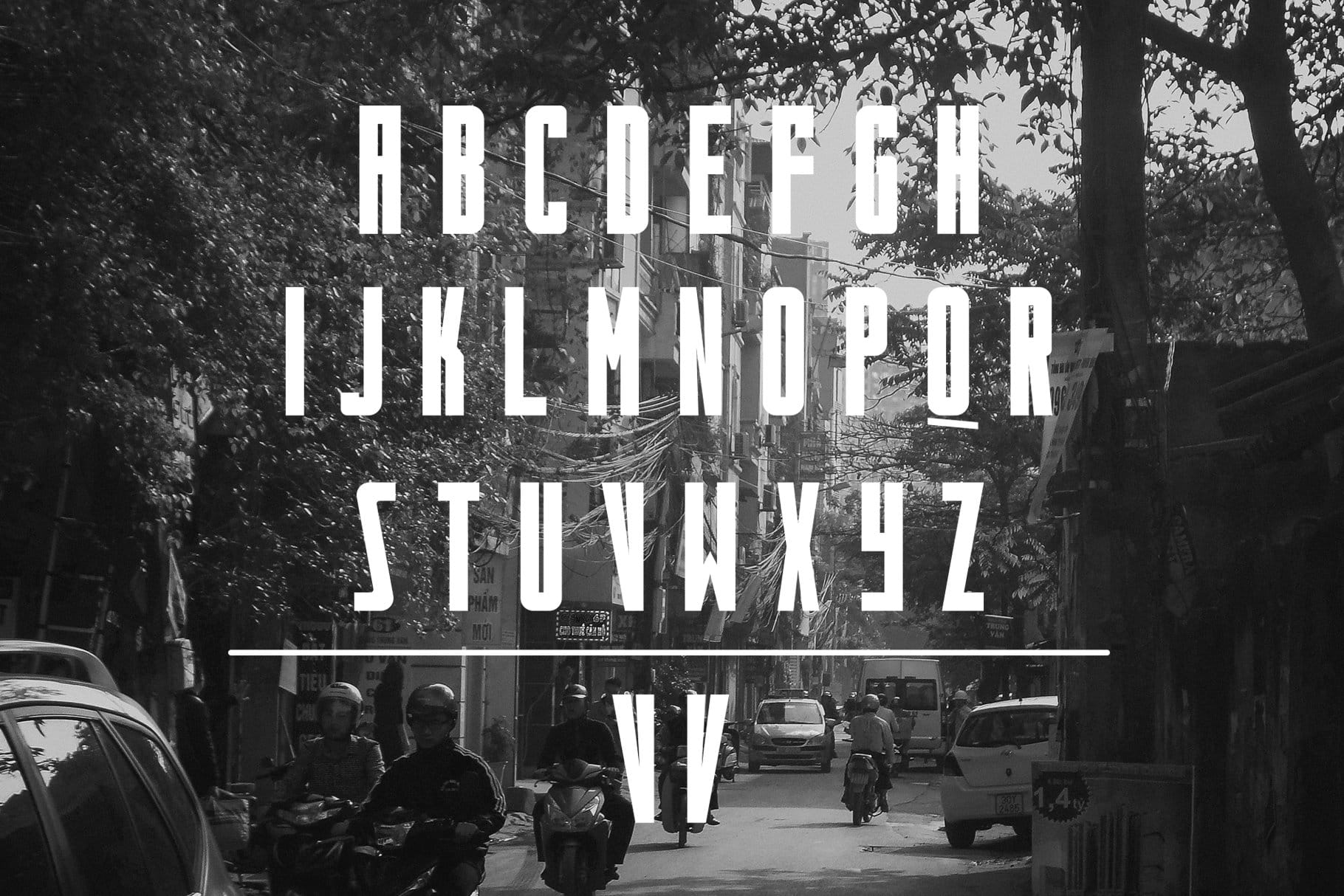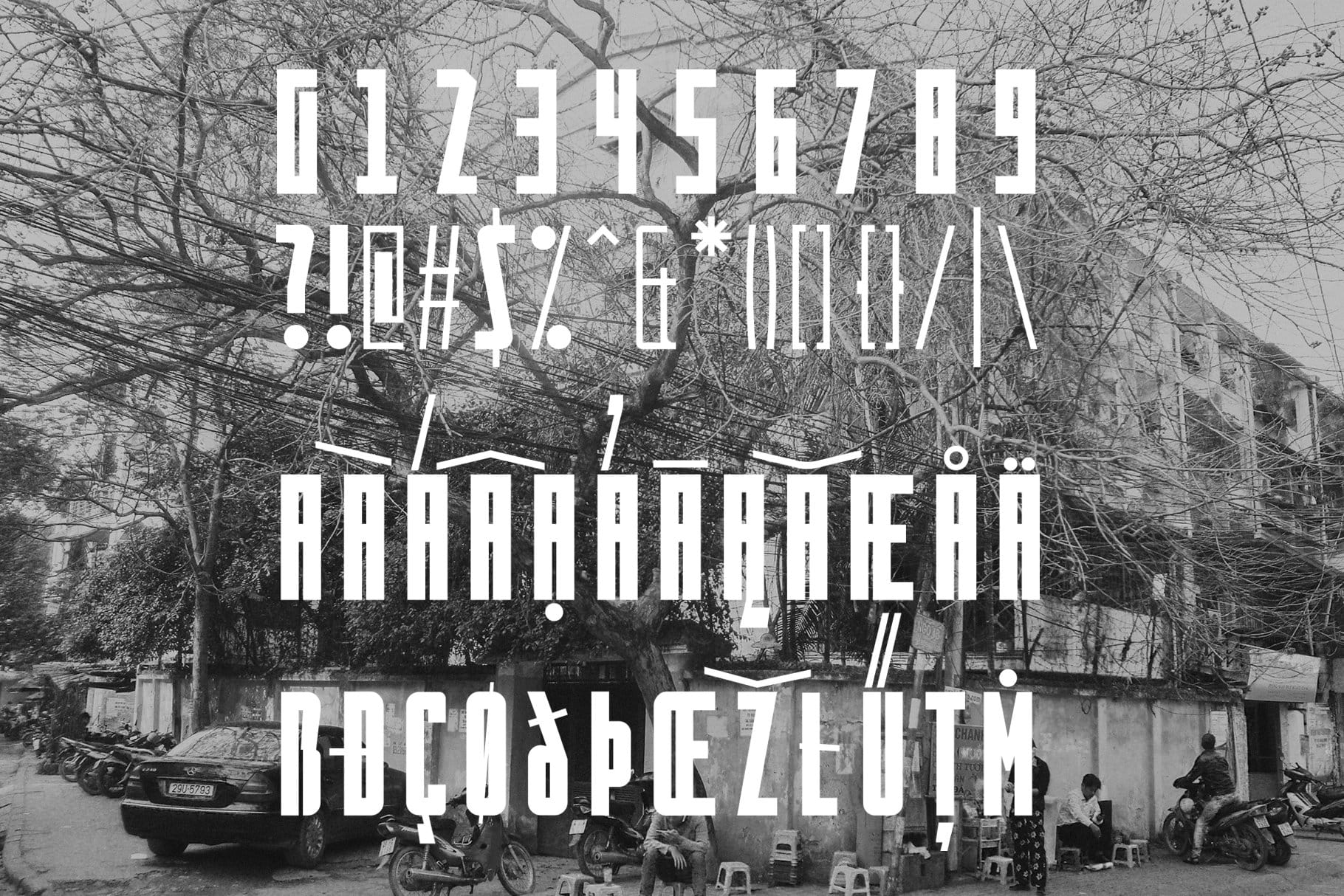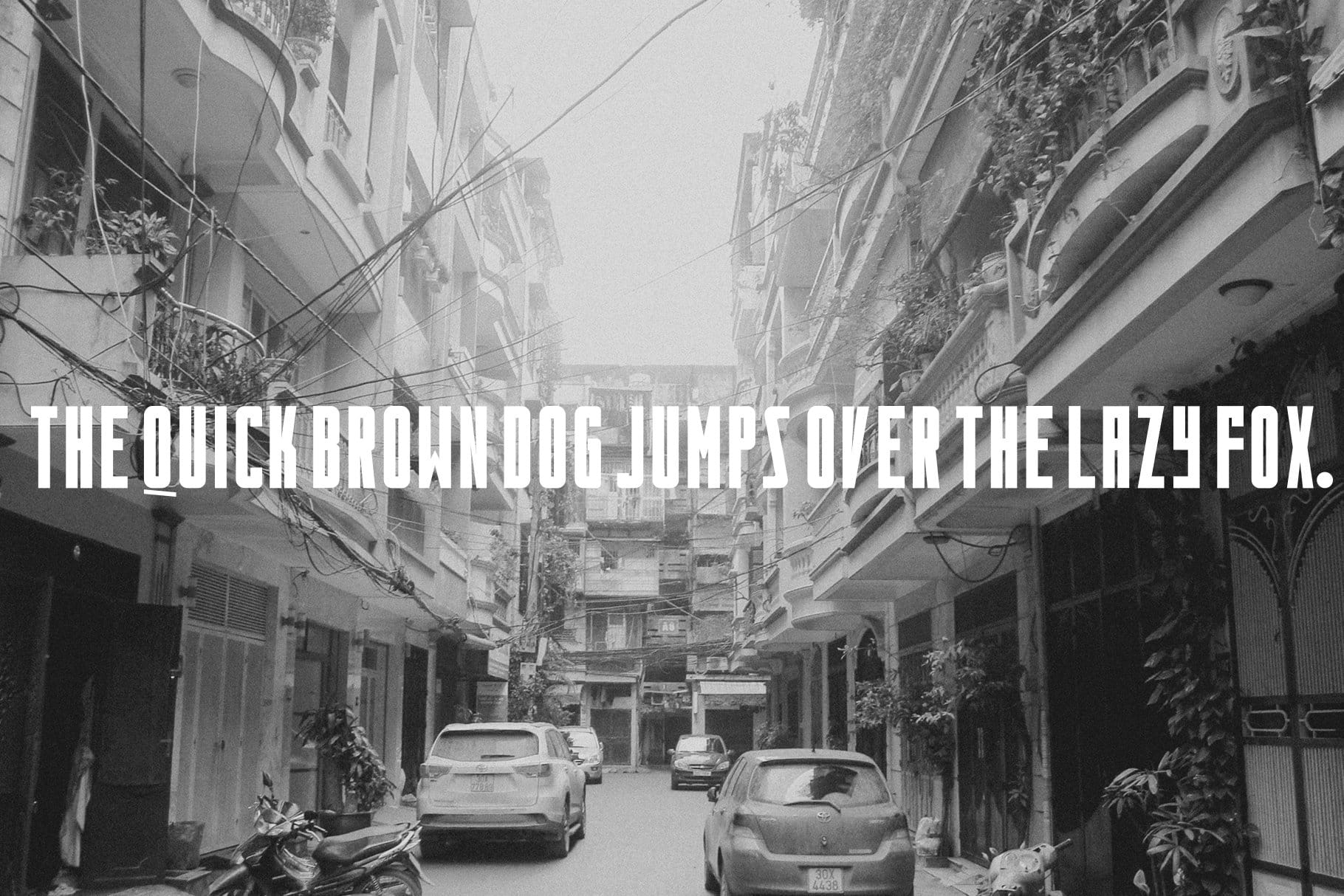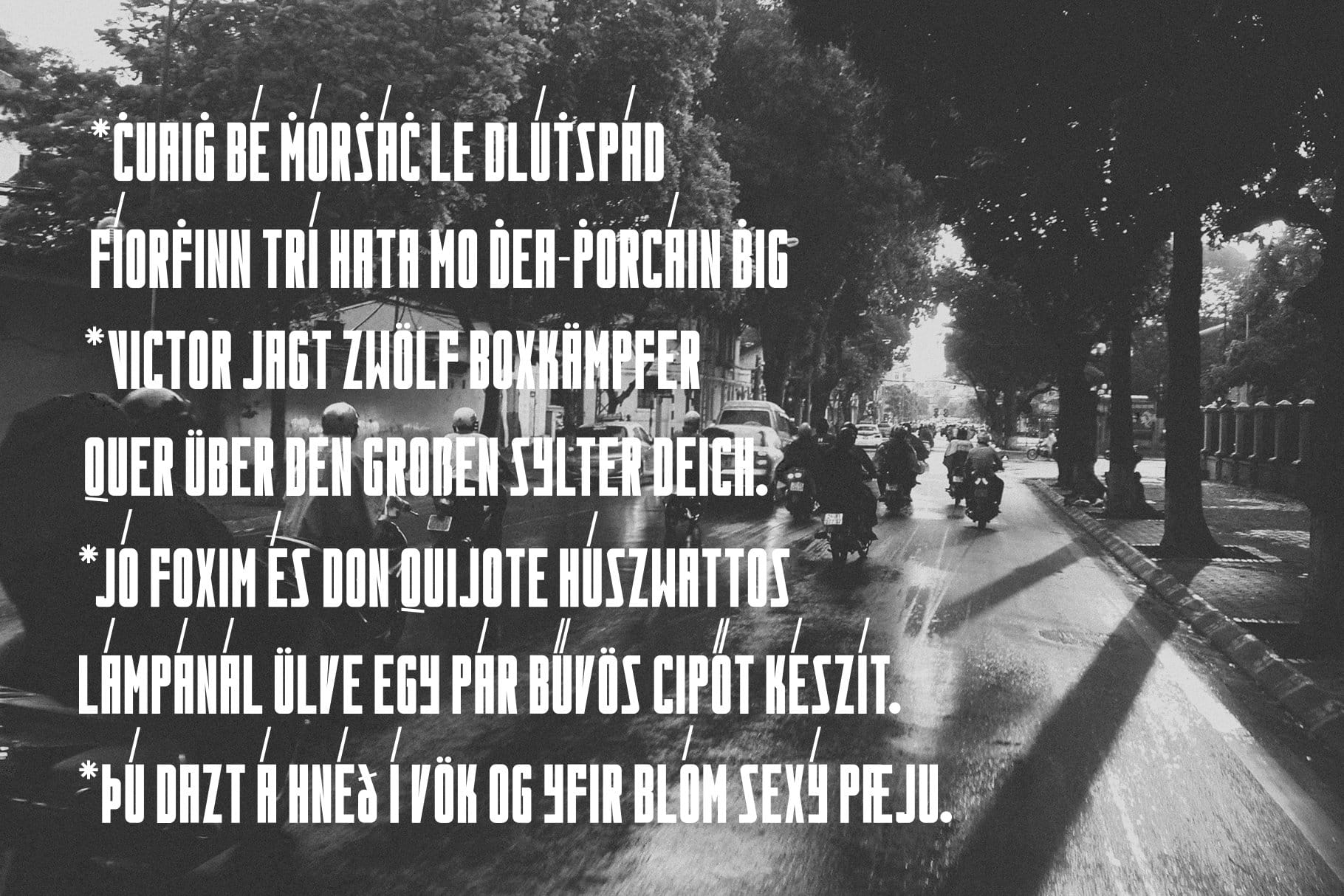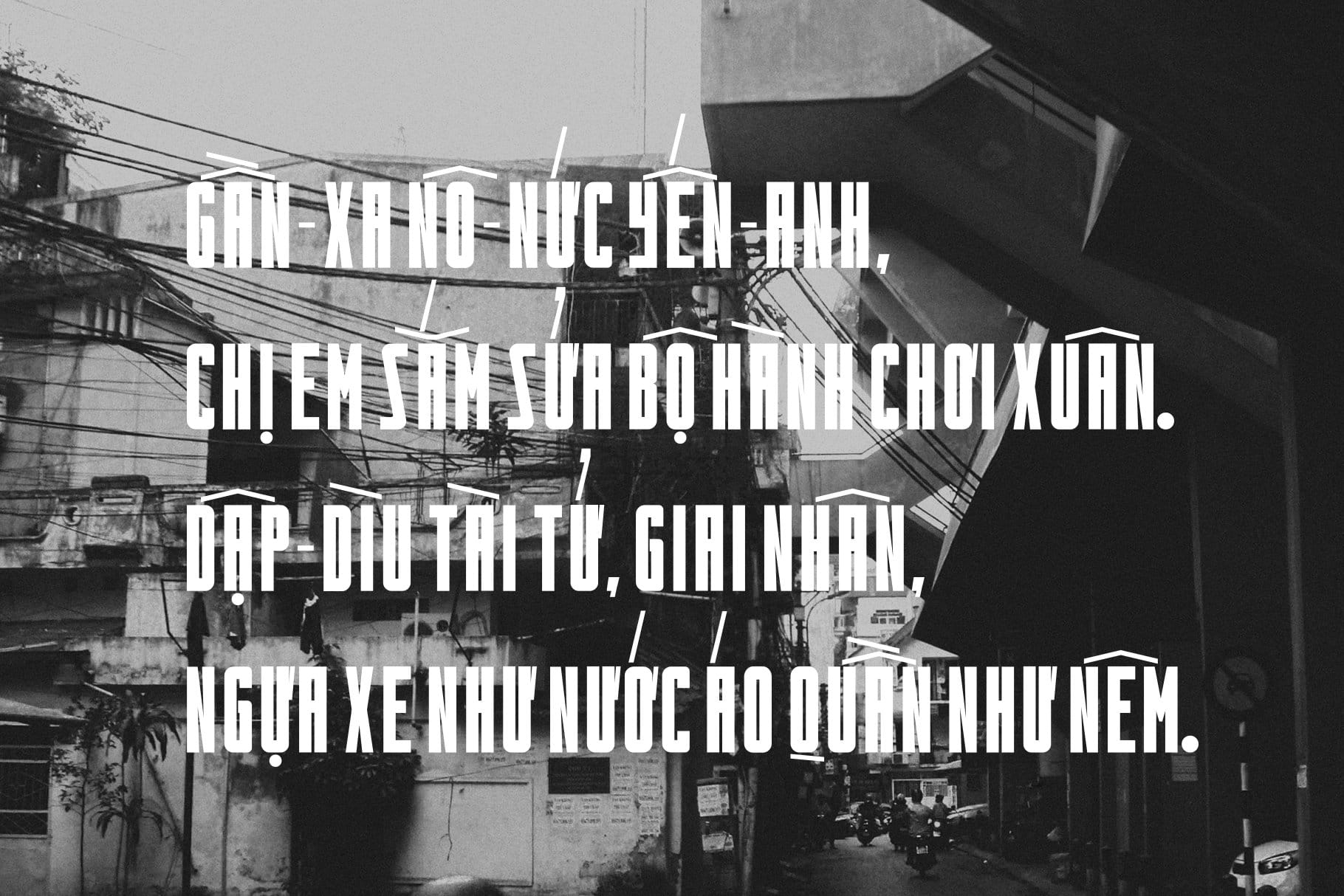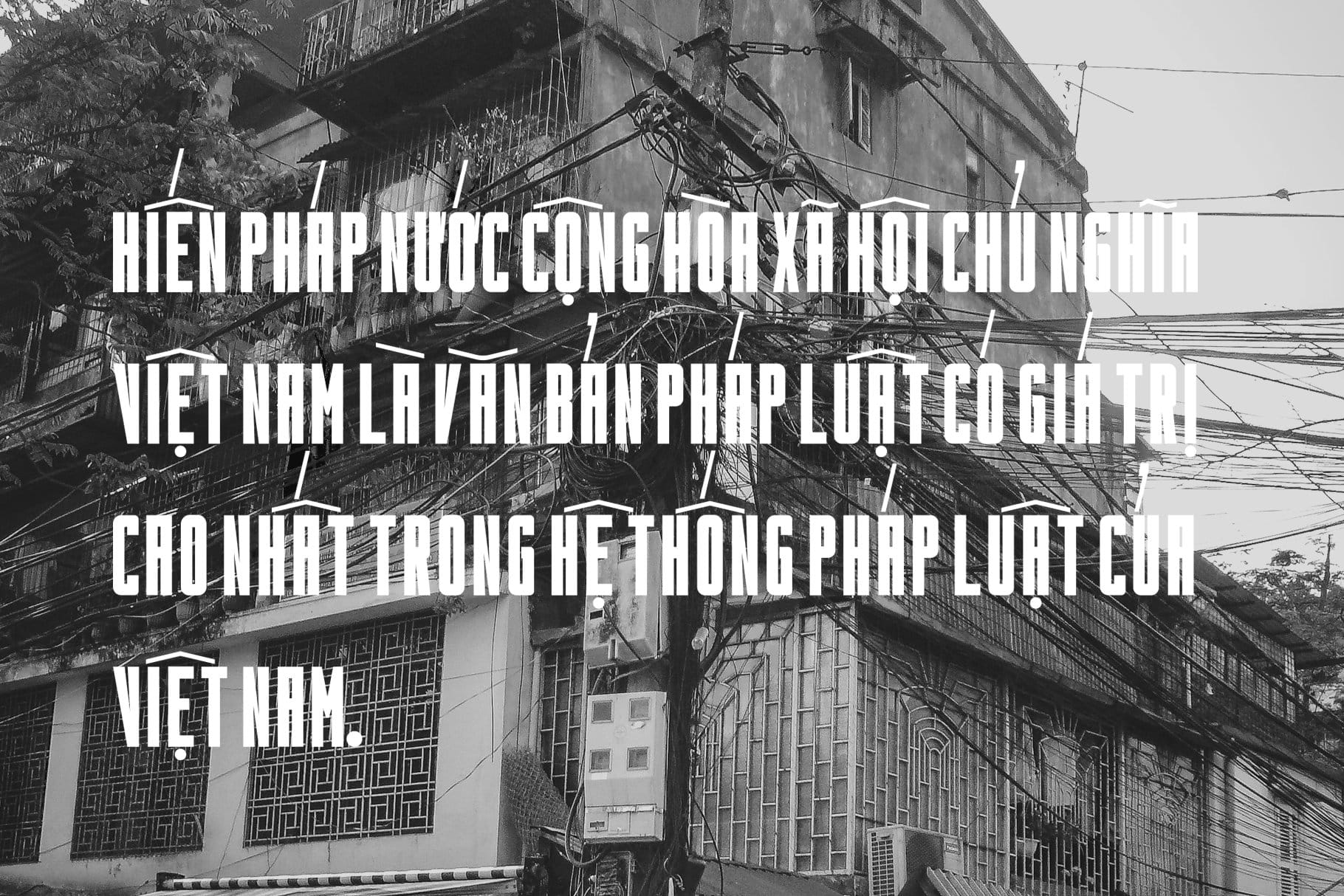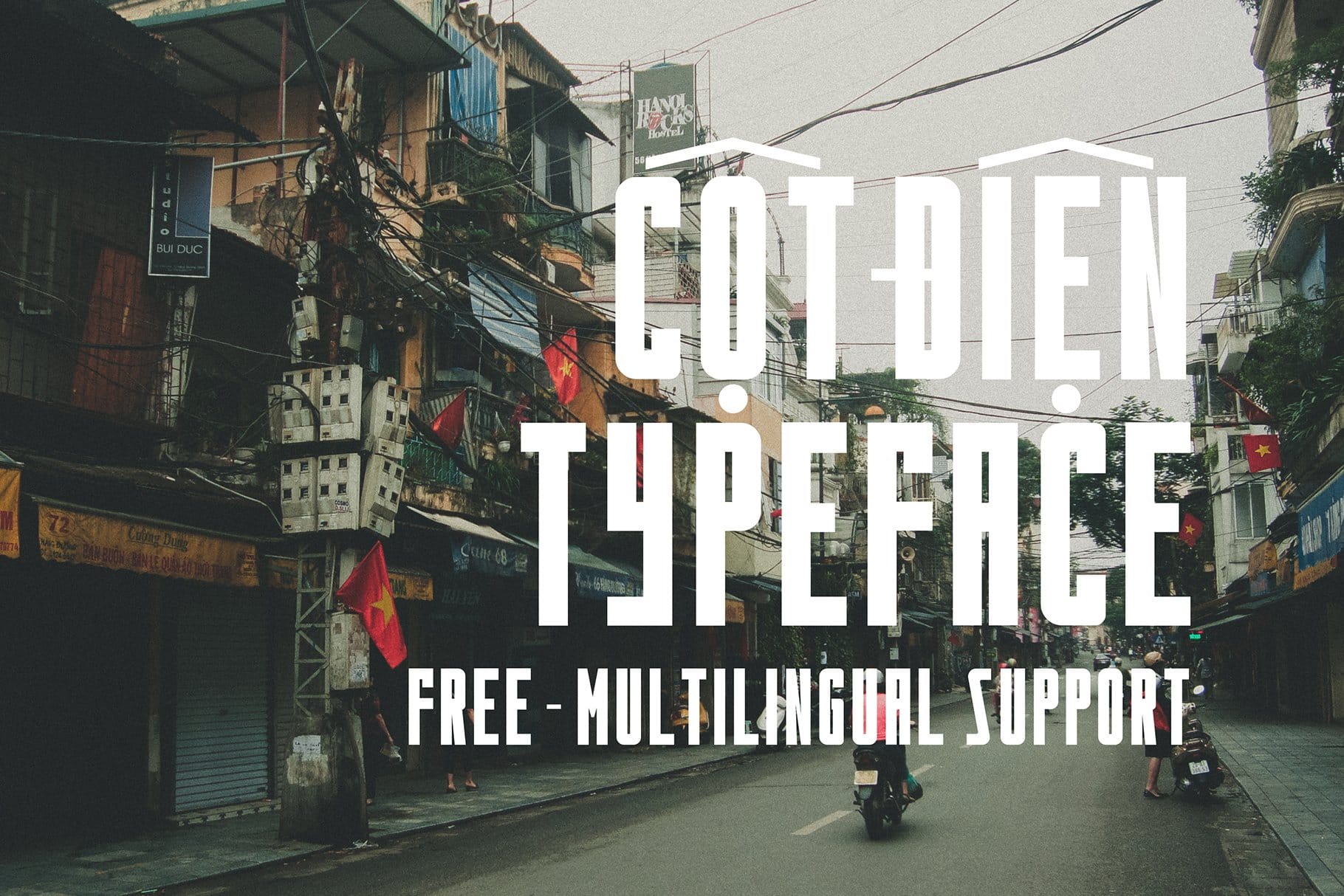
Cotdien Typeface (Cột điện) – là font chữ được tạo ra bởi Manh Nguyen, với phong cách cổ điển theo dạng xưa cũ. Dành cho những người yêu thích các pa nô và biểu ngữ tuyên truyền vẽ tay cổ điển ở Việt Nam từ những thế kỷ trước và cố gắng mang lại cảm giác của một người được vẽ vào tác phẩm của mình.